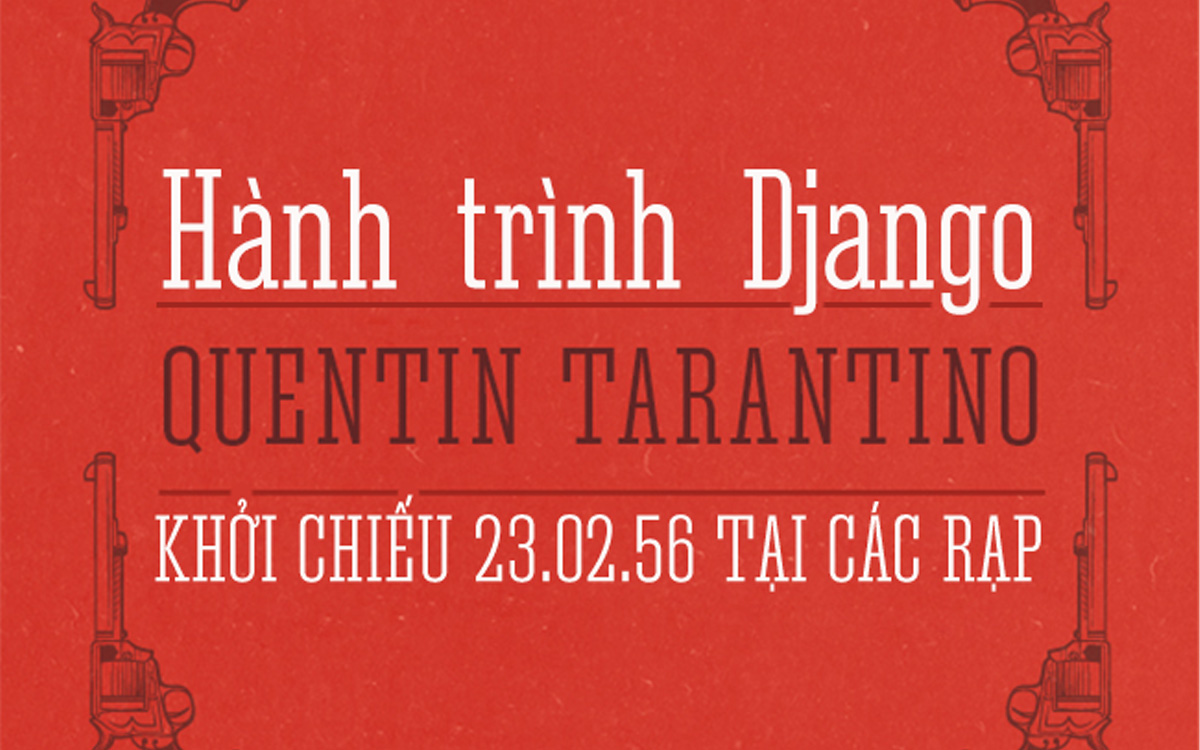
Font chữ thanh lịch, hiện đại, sang trọng dùng cho thiết kế thiệp cưới, thời trang, tạp chí SVN-Corki
Trong thế giới thiết kế đồ họa hiện đại, việc lựa chọn một font chữ phù hợp đóng vai trò quyết định đến cảm xúc và thông điệp mà ấn phẩm muốn truyền tải. SVN-Corki nổi lên như một giải pháp typography hoàn hảo, mang đậm tinh thần nghệ thuật tinh tế và sức hút vượt thời gian. Sự kết hợp khéo léo giữa nét cổ điển quý phái và đường nét tân thời giúp bộ font này trở thành điểm nhấn không thể thiếu cho các nhà thiết kế chuyên nghiệp.
Dù bạn đang thực hiện dự án nhận diện thương hiệu cao cấp, biên tập tạp chí thời trang danh giá hay sáng tạo những mẫu thiệp cưới lãng mạn, SVN-Corki đều có khả năng nâng tầm giá trị thẩm mỹ cho tác phẩm của bạn. Hãy cùng khám phá chi tiết về nét đẹp độc đáo và những tính năng nổi bật mà bộ font chữ này mang lại trong bài viết dưới đây.
Font Chữ Thanh Lịch, Hiện Đại, Sang Trọng SVN-Corki – Lựa Chọn Đẳng Cấp Cho Thiết Kế Thiệp Cưới, Thời Trang Và Tạp Chí
Font chữ SVN-Corki là bản Việt hóa hoàn chỉnh của dòng font cao cấp, được tinh chỉnh tỉ mỉ từng dấu thanh để phục vụ tối đa cho ngôn ngữ tiếng Việt. Với định hướng thẩm mỹ nhắm vào sự sang trọng, tinh tế và tính hiện đại, SVN-Corki tôn vinh vẻ đẹp của từng chữ cái thông qua tỷ lệ hình học chuẩn xác và sự cân bằng thị giác tuyệt vời. Đây không chỉ đơn thuần là một công cụ hiển thị văn bản, mà còn là một tác phẩm nghệ thuật giúp nâng tầm mọi ý tưởng sáng tạo đồ họa.
1. Đường Nét Thiết Kế Serif Tinh Tế Và Tỷ Lệ Hình Học Hiện Đại
Điểm đặc trưng đầu tiên giúp SVN-Corki ghi điểm tuyệt đối trong mắt các designer chính là cấu trúc nét chữ được gọt giũa vô cùng công phu. Bộ font sở hữu sự tương phản hài hòa giữa các nét thanh và nét đậm, tạo nên hiệu ứng thị giác cuốn hút nhưng vẫn giữ được độ đọc tốt ở mọi kích thước.
Chân chữ (serif) của SVN-Corki được dải mỏng nhẹ, dứt khoát, mang lại cảm giác thanh thoát chứ không hề nặng nề như các dòng font cổ điển truyền thống. Sự pha trộn giữa yếu tố tân cổ điển và hơi thở hiện đại giúp font chữ này dễ dàng làm nổi bật các tiêu đề lớn, logo hay các đoạn slogan mang tính biểu tượng.
• Độ tương phản nét chữ lý tưởng: Tạo chiều sâu và sự quyến rũ cho phần tiêu đề ấn phẩm.
• Khoảng cách khoảng trống (Kerning) tối ưu: Giúp các ký tự đứng cạnh nhau một cách nhịp nhàng, tự nhiên.
• Kiểu dáng thời thượng: Thích hợp cho cả phong cách tối giản (Minimalism) lẫn phong cách nghệ thuật cầu kỳ (Art Deco).
2. Giải Pháp Hoàn Hảo Cho Thiết Kế Thiệp Cưới Và Ấn Phẩm Sự Kiện Cao Cấp
Trong ngành thiết kế thiệp cưới, yếu tố lãng mạn, thanh lịch và chỉn chu luôn được đặt lên hàng đầu. SVN-Corki đáp ứng trọn vẹn những yêu cầu khắt khe đó nhờ vào thần thái sang trọng, ấm áp và vô cùng tinh tế mà nó mang lại cho tấm thiệp mời.
Khi được ứng dụng lên tên chú rể – cô dâu, ngày kỷ niệm hay các dòng chữ trích dẫn tình yêu, SVN-Corki biến những dòng chữ khô khan thành những nét vẽ biết nói. Font chữ này kết hợp cực kỳ ăn ý với các kỹ thuật in ấn cao cấp như ép kim (foiling), dập nổi (embossing), in UV hoặc sử dụng trên các chất liệu giấy mỹ thuật cao cấp, giấy nến và lụa.
Ngoài thiệp cưới, SVN-Corki cũng là sự lựa chọn số một cho các loại thiệp mời sự kiện gala, tiệc tối sang trọng, menu nhà hàng 5 sao và thẻ vị trí khách mời cao cấp.
3. Tối Ưu Cho Ngành Thời Trang, Tạp Chí Và Nhận Diện Thương Hiệu Luxury
Đối với ngành công nghiệp thời trang và truyền thông tạp chí, font chữ chính là “gương mặt đại diện” thể hiện gu thẩm mỹ và đẳng cấp của thương hiệu. SVN-Corki thể hiện xuất sắc vai trò này khi xuất hiện trên các trang bìa tạp chí, bộ bộ sưu tập Lookbook, banner quảng cáo mỹ phẩm hay nước hoa đắt tiền.
Vẻ đẹp hiện đại và kiêu sa của SVN-Corki giúp truyền tải thông điệp về sự độc bản, thời thượng và xa xỉ. Các thương hiệu thời trang cao cấp, spa làm đẹp, tiệm trang sức hay bất động sản hạng sang thường xuyên ứng dụng bộ font này vào hệ thống nhận diện thương hiệu để khẳng định vị thế dẫn đầu.
1. Trang bìa tạp chí: Tạo điểm nhấn thu hút ngay từ cái nhìn đầu tiên với các tiêu đề lớn bay bổng.
2. Bao bì sản phẩm: Nâng tầm giá trị hộp quà, chai nước hoa, mỹ phẩm cao cấp.
3. Logo & Branding: Xây dựng bộ nhận diện thương hiệu nhất quán, chuyên nghiệp và thanh lịch.
4. Bộ Ký Tự Tiếng Việt Hóa Chuẩn Xác Và Đầy Đủ Glyphs Nghệ Thuật
Một trong những ưu điểm lớn nhất của SVN-Corki chính là việc đã được Việt hóa trọn bộ với chuẩn Unicode. Các dấu thanh tiếng Việt (sắc, huyền, hỏi, ngã, nặng và các dấu ô, ê, ơ, ư…) được thiết kế tinh xảo, giữ nguyên tỉ lệ và phong cách của bản gốc mà không làm mất đi tính thẩm mỹ tổng thể của từ ngữ.
Bên cạnh đó, bộ font còn tích hợp nhiều ký tự thay thế (Alternate Glyphs) và nét nối nghệ thuật (Ligatures). Điều này cho phép các nhà thiết kế tự do sáng tạo, biến tấu các chữ cái để tạo ra những cụm từ độc nhất vô nhị mà không lo bị trùng lặp hay đơn điệu.